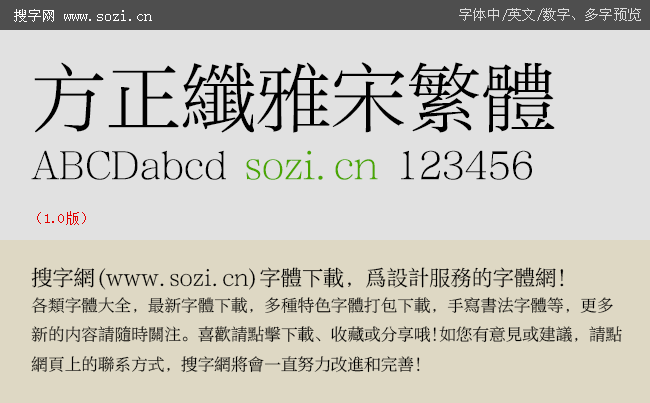
方正纖雅宋繁體(FZXYSFW)
搜字網(wǎng)提供一款方正纖雅宋繁體中文字體下載,方正纖雅宋是一款字形清秀的中文字體,該字體端正大方,纖細(xì)秀美,結(jié)構(gòu)清晰,效果出眾,常用于產(chǎn)品設(shè)計(jì)、包裝印刷、報(bào)刊雜志、正文標(biāo)題、繪畫(huà)創(chuàng)作等廣告設(shè)計(jì)場(chǎng)合使用。